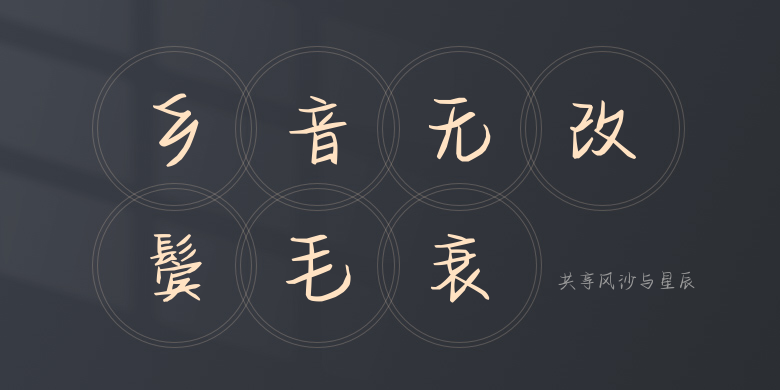
共享风沙与星辰
共享风沙与星辰,这款字体结构工整、笔画清晰,兼顾美观与易读性,适用于标题、正文、海报、包装、LOGO 等多种场景。字形优雅稳定,风格百搭耐看,适配日常排版与创意设计,让文字呈现更舒适、更具质感。共享风沙与星辰一笔一画,皆是细节,以均衡的比例、流畅的线条打造舒适视觉体验,字形端正大气,风格简约现代。无论是商业设计、品牌宣传还是日常排版,都能轻松驾驭,让文字更有格调与力量。共享风沙与星辰字体下载。